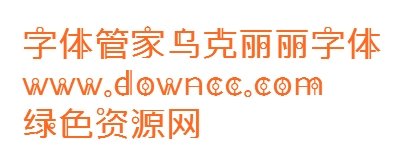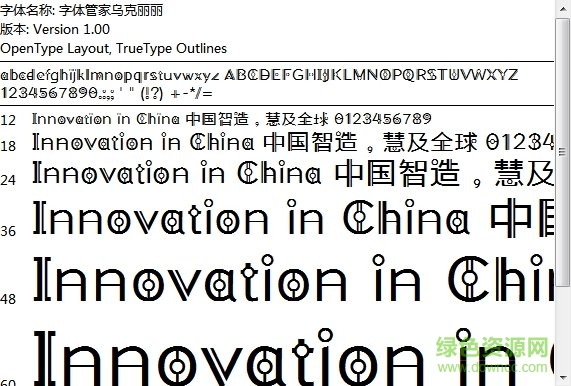
aa烏克麗麗字體是字體管家推出的一款可愛(ài)藝術(shù)字體,將一些漢字或字母變成琴弦圖案,更有音樂(lè)節(jié)奏感,讓文字生動(dòng)起來(lái),綠色資源網(wǎng)今日推薦!
你就是海灘下的那烏克麗麗,尋找著逆光讓曖昧變成剪影。這款字體的靈感來(lái)自音樂(lè),在簡(jiǎn)單的黑體基礎(chǔ)上,增添雙線與空心圓,簡(jiǎn)單的元素,卻讓人聯(lián)想到樂(lè)器的簡(jiǎn)筆構(gòu)型。靈感來(lái)源于現(xiàn)今流行的烏克麗麗,簡(jiǎn)化出具有獨(dú)特風(fēng)格的元素,運(yùn)用到字體當(dāng)中,進(jìn)行創(chuàng)作。